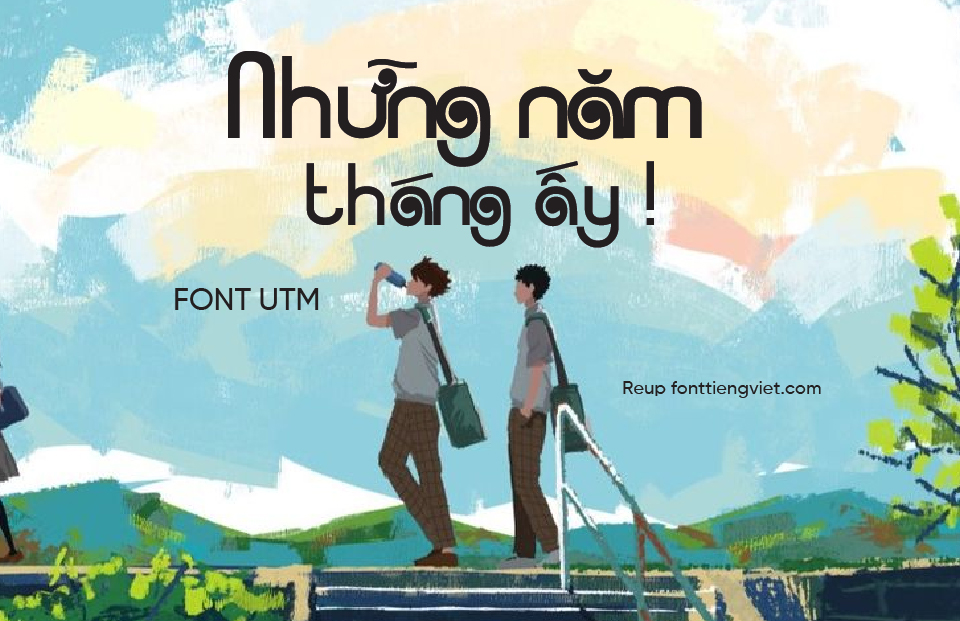
Font việt hóa UTM Arruba KT
Giới thiệu về bộ Font việt hóa UTM Arruba KT
Trong thế giới đồ họa hiện đại, việc lựa chọn một Font Miễn Phí phù hợp đóng vai trò then chốt giúp truyền tải thông điệp hiệu quả. Font việt hóa UTM Arruba KT là một trong những phông chữ thuộc bộ UTM nổi tiếng, được tinh chỉnh hoàn toàn để tương thích với bảng mã tiếng Việt. Với những đường nét thanh mảnh nhưng không kém phần cứng cáp, mẫu chữ này mang đến sự cân bằng hoàn hảo giữa tính nghệ thuật và khả năng đọc hiểu. Đây là lựa chọn lý tưởng cho những ai đang tìm kiếm sự mới mẻ trong thiết kế mà vẫn giữ được nét thanh lịch cần thiết.
Đặc điểm nổi bật của Font việt hóa UTM Arruba KT
Phong cách thiết kế độc đáo
Điểm mạnh nhất của Font việt hóa UTM Arruba KT chính là cấu trúc ký tự được xây dựng tỉ mỉ. Các nét chữ có độ dày vừa phải, tạo cảm giác hiện đại và chuyên nghiệp. Điều này giúp bộ font dễ dàng ứng dụng trong nhiều dự án khác nhau từ học đường đến công việc văn phòng.
Tính ứng dụng đa dạng trong cuộc sống
Học sinh và giáo viên có thể sử dụng font chữ này để làm slide bài giảng, thiệp chúc mừng hoặc các ấn phẩm truyền thông nhỏ trong trường học. Độ tương phản của chữ giúp hiển thị rõ nét trên cả màn hình máy tính lẫn khi in ra giấy, đảm bảo nội dung luôn được truyền đạt một cách rõ ràng nhất đến người xem.
Hướng dẫn sử dụng và kết luận